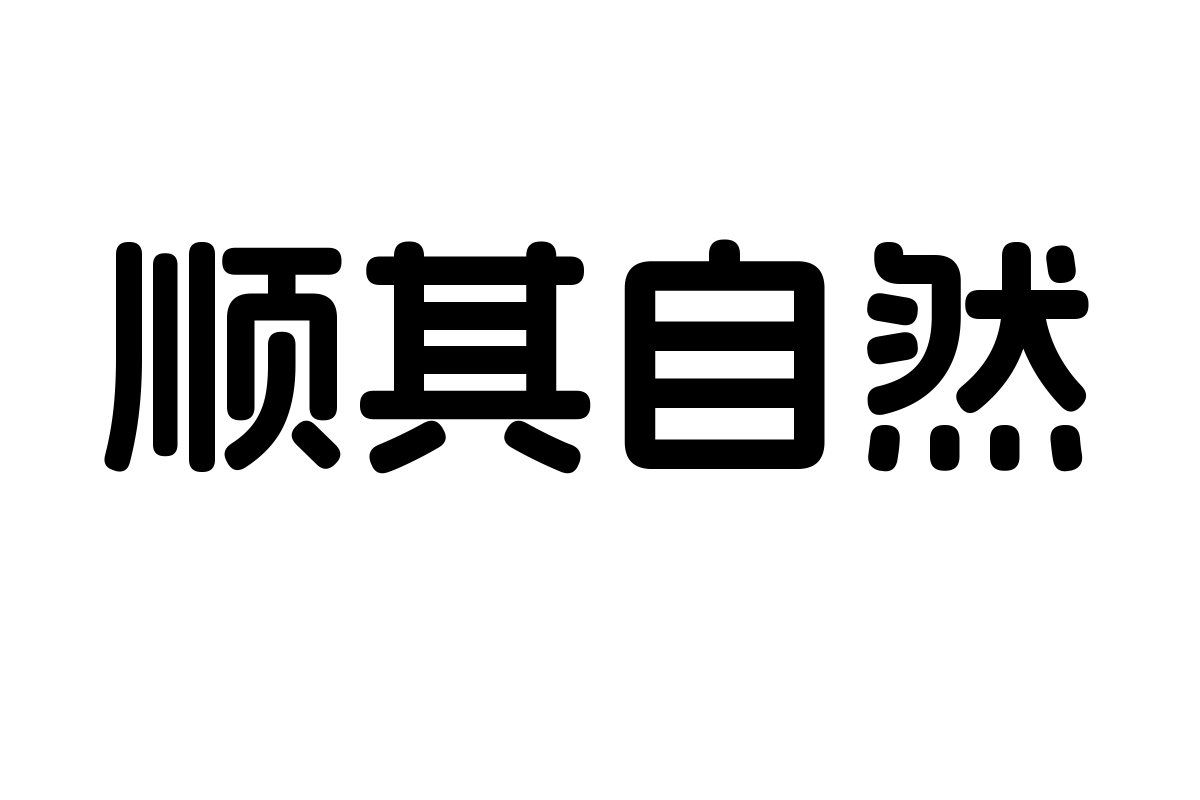
阿里妈妈方圆体是一种具有现代感的中文字体,由阿里巴巴旗下的阿里妈妈团队开发。该字体设计独特,线条流畅,结构紧凑,给人一种简洁、明快的感觉。
阿里妈妈方圆体的笔画粗细适中,既有粗犷的线条,又有细腻的转折,使得整个字体既富有力量感,又不失柔和感。同时,该字体还注重细节的处理,如笔画的连接处、字与字之间的间距等,都经过精心的设计,使得整体视觉效果更加和谐统一。
此外,阿里妈妈方圆体还具有一定的可读性,无论是在印刷品上还是在网络上,都能保持良好的视觉效果。这使得该字体在广告、包装、书籍等领域得到了广泛的应用。
总的来说,阿里妈妈方圆体以其独特的设计风格和良好的视觉效果,成为了一种备受欢迎的中文字体。
阿里妈妈方圆体